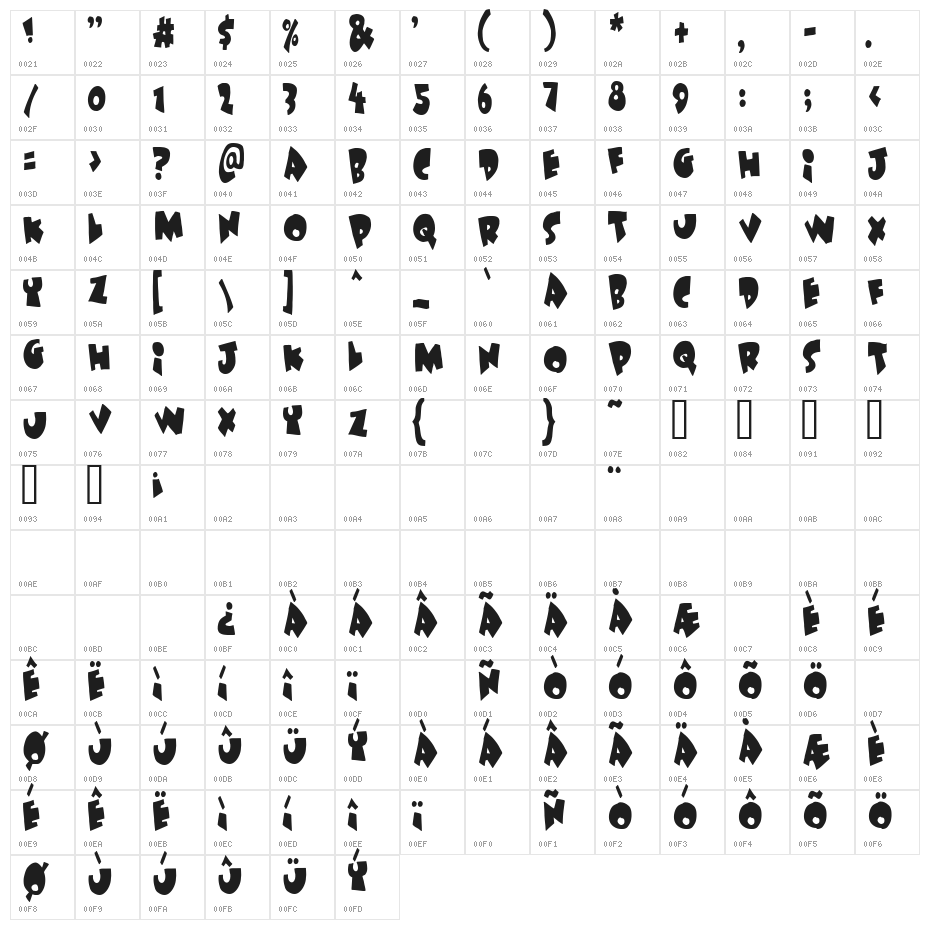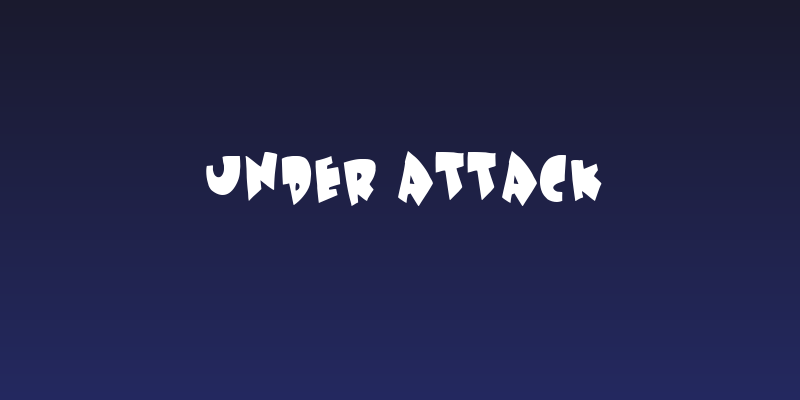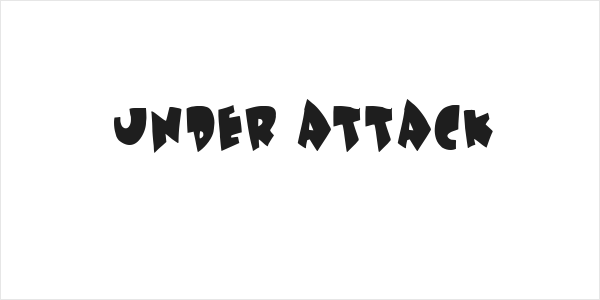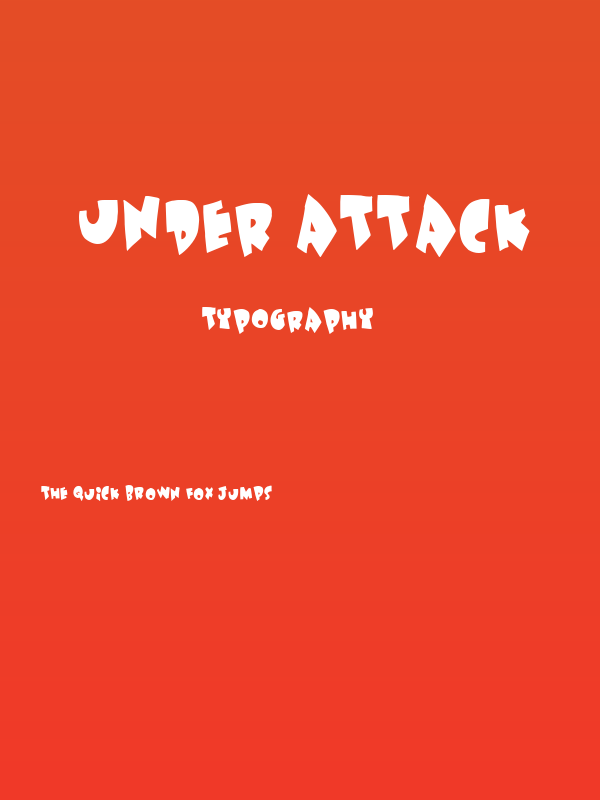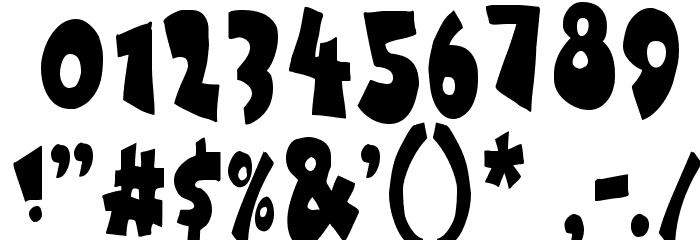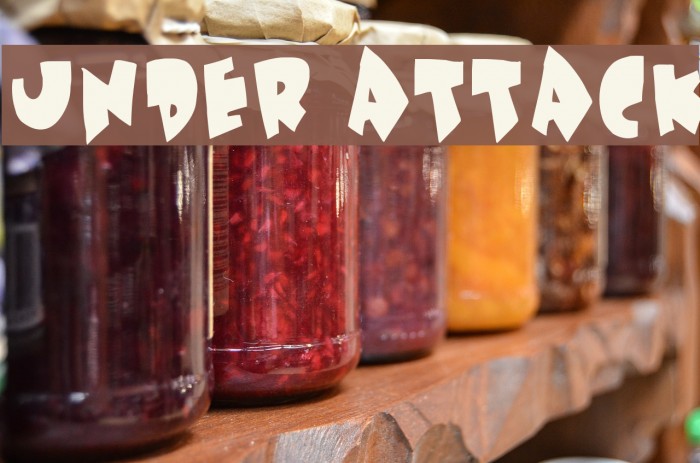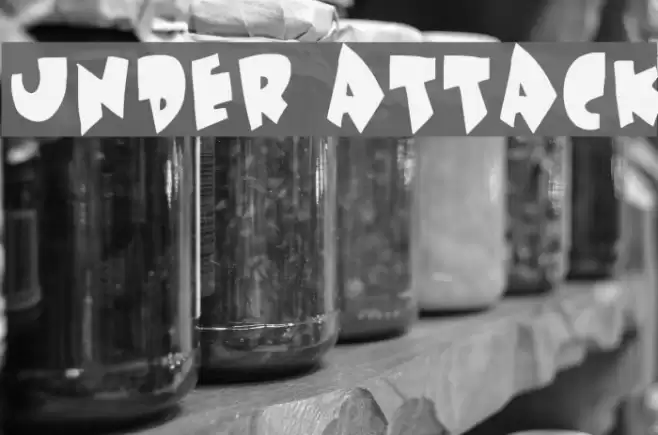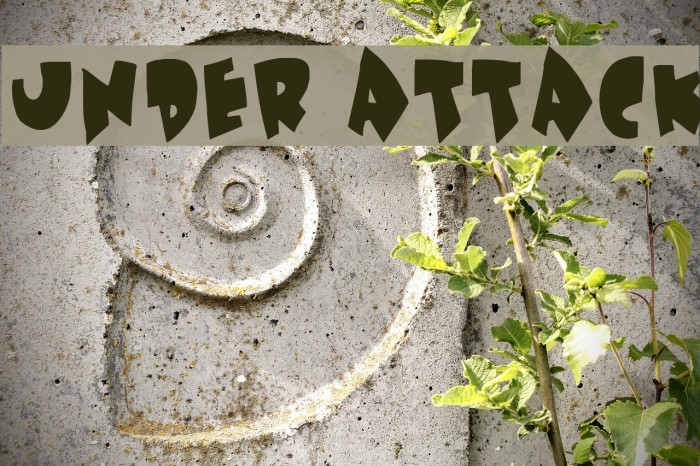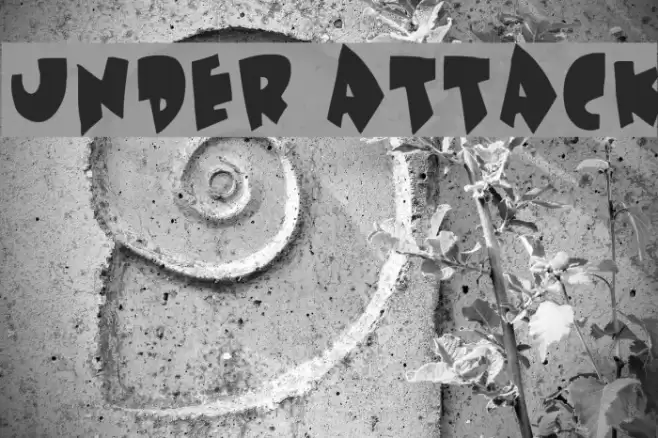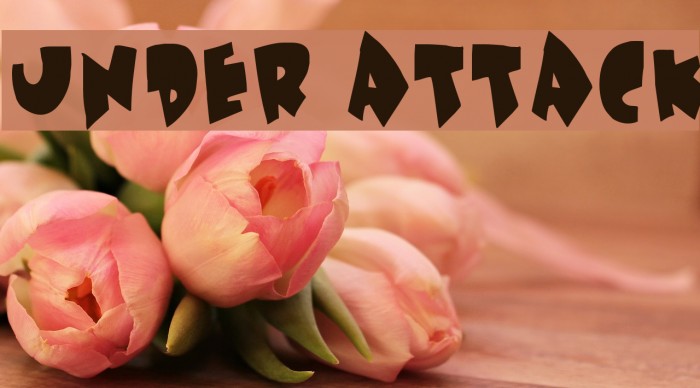
Under attack Font
| Style général | Playful, Energetic, Dynamic |
| Projets proposés | Ideal for children's books, comic strips, playful branding, and eye-catching posters. |